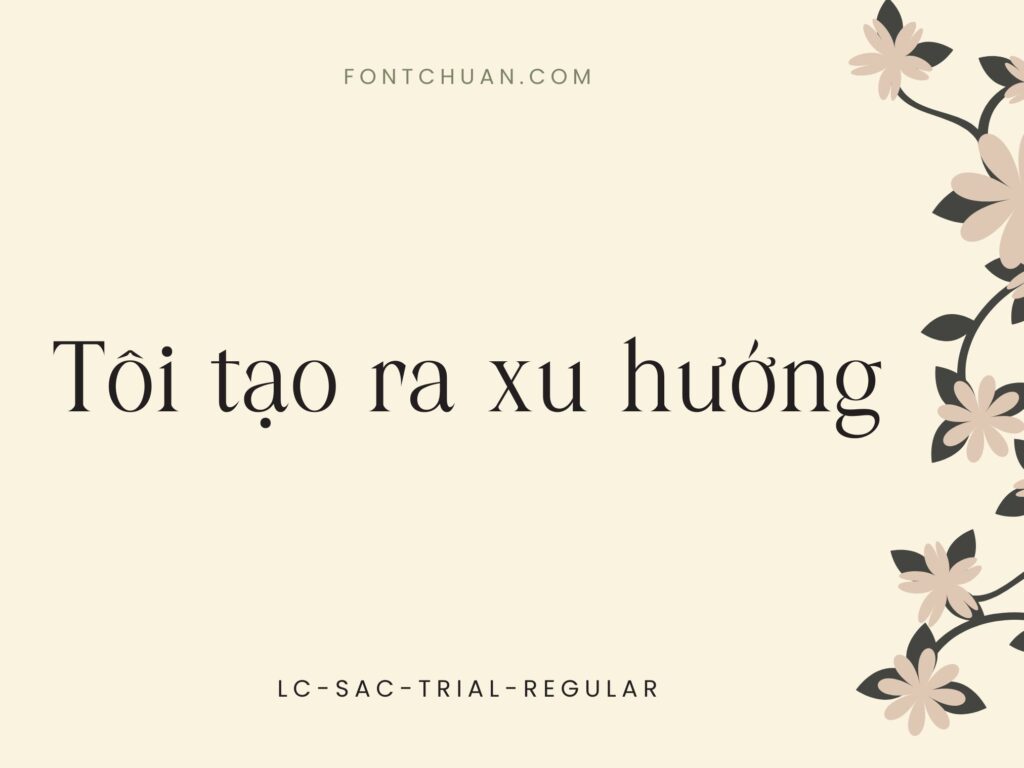
Font Lc Sac Display Font Tiếng Việt
Tác giả Font: Nguyễn Quang Duy
Việt hóa bởi: Nguyễn Quang Duy
LC Sac là một phông chữ serif trang trí với vẻ ngoài thanh lịch và tinh tế, được thiết kế bởi Dsuy Nguyen. Trong tiếng Việt, “Sắc” có nghĩa là vẻ đẹp và sự sắc sảo. LC Sac Display được lấy cảm hứng mạnh mẽ từ các chữ cái La Mã vuông ở thế kỷ thứ 4 với các chân chữ rất sắc nét. Trong suốt quá trình thiết kế, một số chi tiết hiện đại đã được phát triển một cách tỉ mỉ để tôn lên đặc tính của nó. Phông chữ này hỗ trợ đa ngôn ngữ, bao gồm cả tiếng Việt, mở rộng khả năng ứng dụng trong các dự án quốc tế. Việc hỗ trợ tiếng Việt giúp người dùng Việt Nam trải nghiệm gõ chữ trọn vẹn và dễ dàng tích hợp vào các thiết kế địa phương. LC Sac đã được thành viên của Font Chuẩn chọn lọc và sưu tầm, nhằm đáp ứng nhu cầu bạn đọc và ứng dụng thực tế vào các dự án thiết kế.
Về đặc điểm thiết kế, LC Sac có cấu trúc serif trang trí với các chân chữ sắc nét và hình dáng tinh tế, tạo cảm giác cổ điển nhưng vẫn hiện đại. Phông chữ này phù hợp cho các ứng dụng như thiết kế logo, tiêu đề, thương hiệu lấy cảm hứng cổ điển, biển hiệu và các dự án sáng tạo khác. LC Sac cũng thích hợp cho các thiết kế cần sự tinh tế và hiện đại, như áp phích quảng cáo, bao bì sản phẩm và các dự án truyền thông. Về ngành nghề, LC Sac đặc biệt phù hợp với lĩnh vực quảng cáo, công nghệ, giáo dục và các ngành nghề cần sự sáng tạo và hiện đại trong thiết kế. Sự linh hoạt và tinh tế của phông chữ giúp nó dễ dàng hòa nhập vào nhiều phong cách thiết kế khác nhau, từ cổ điển đến hiện đại.